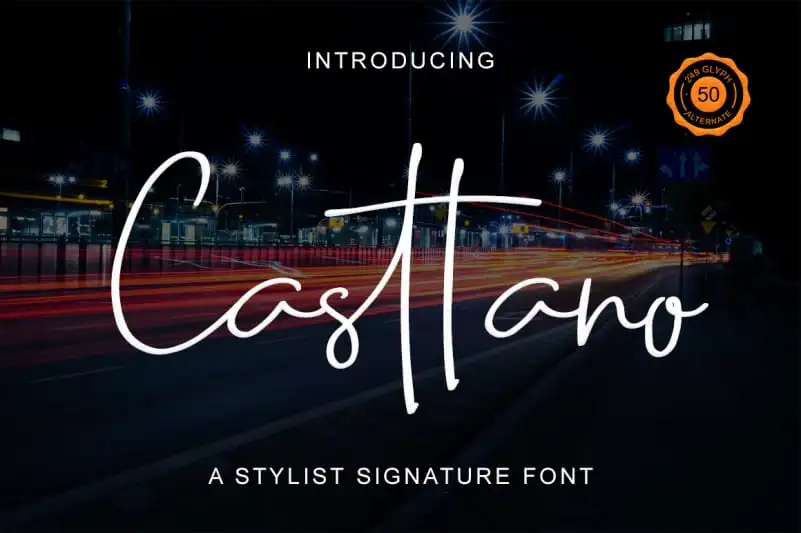
Casttano Handwritten Font – Download Grátis
A Casttano é uma elegante e leve fonte escrita a mão, repleta de charme. Perfeita para adicionar uma pitada autêntica às mais variadas criações gráficas. Seja ela um website profissional, um layout de newsletter ou até mesmo as capas de revistas – a Casttano trará seu design à vida com uma sensação única e intrigante. Esta fonte escrita a mão, criada pelo designer bearydsgn, é perfeita para quem busca agregar personalidade e emoção a seus trabalhos visuais. Não deixe que seu projeto se transforme em apenas mais um item de lista, permita que ele se destaque com a Casttano, uma escolha certeira na sua próxima criação visual.